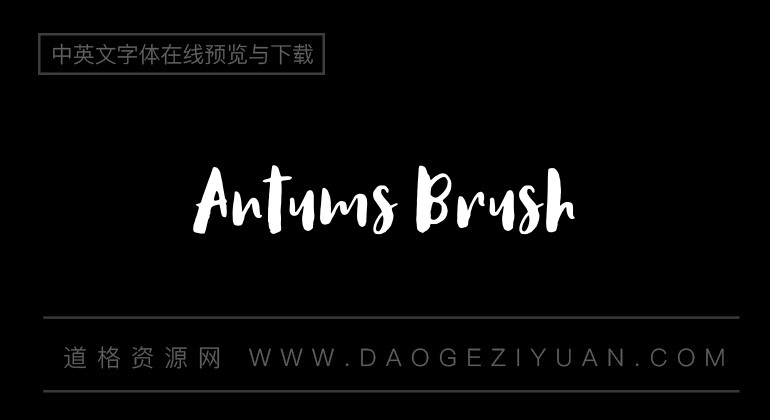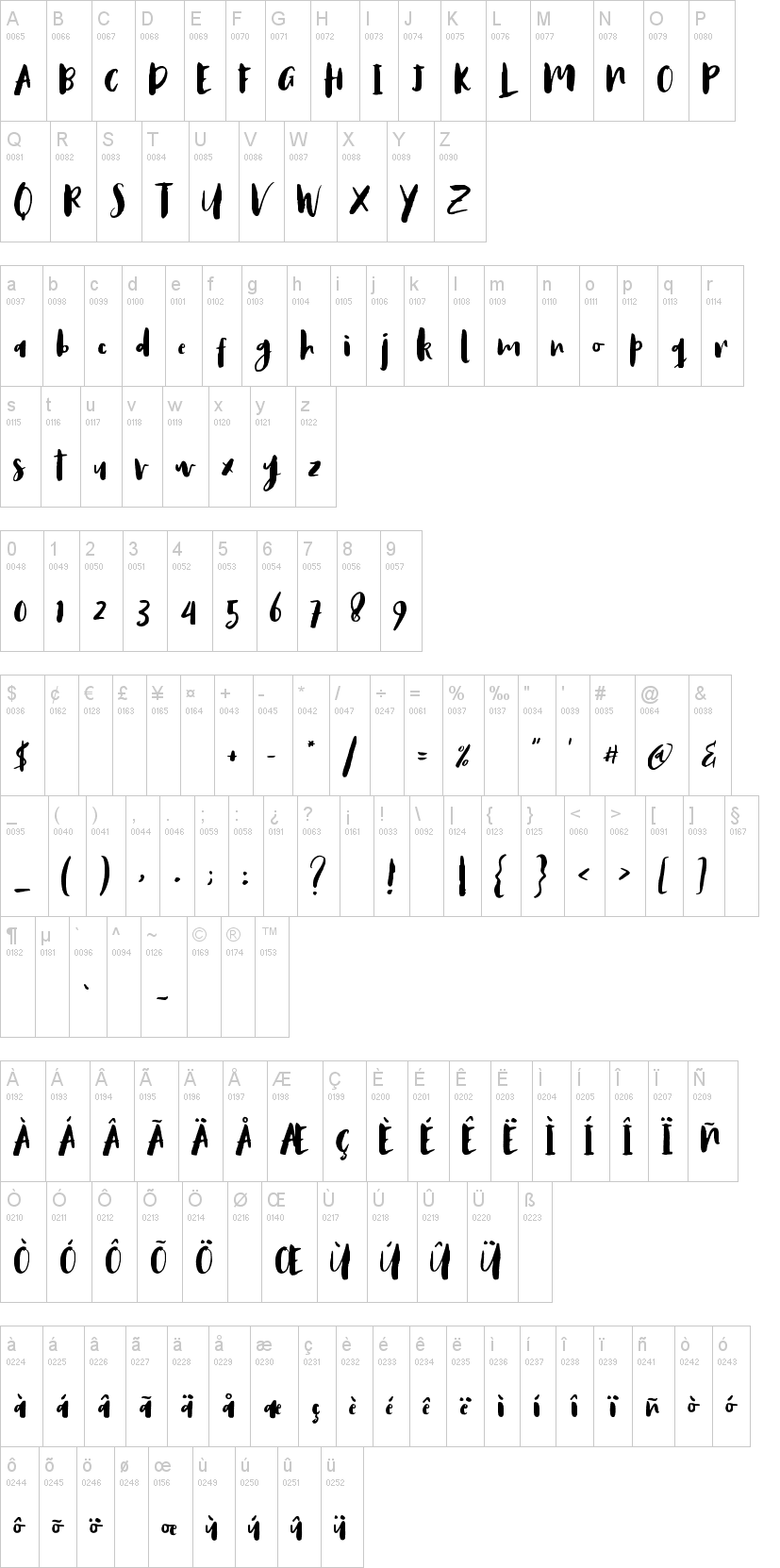
Antums Brush 是一款经典的手写字体,它具有流畅的笔触,温暖的气氛,把握着柔和的线条,给人一种温柔、活泼、清新的感觉。它灵活地反映出文字的节奏感,以及文字之间的联系,更能把握着文字的表达能力。它的笔画细腻,曲线优美,给人一种温暖的感觉,使用它可以让你的文字更有趣,更有魅力。内容介绍
Antums Brush是一款非常不错的手写艺术字体,具有很好的视觉感,适合于文化类的宣传设计、商业类品牌的广告和产品包装设计以及个性化文字排版等较多场景。